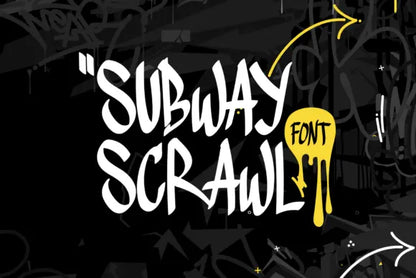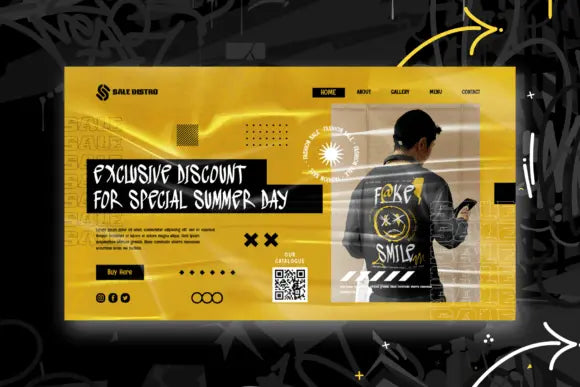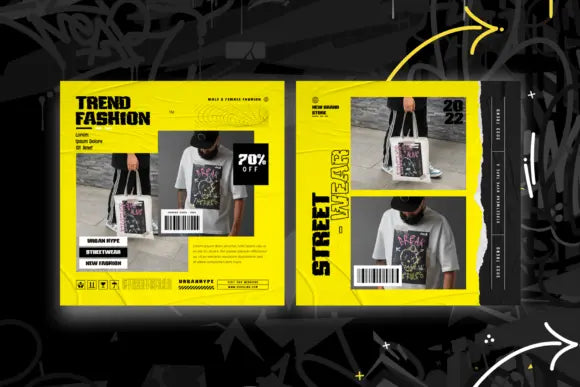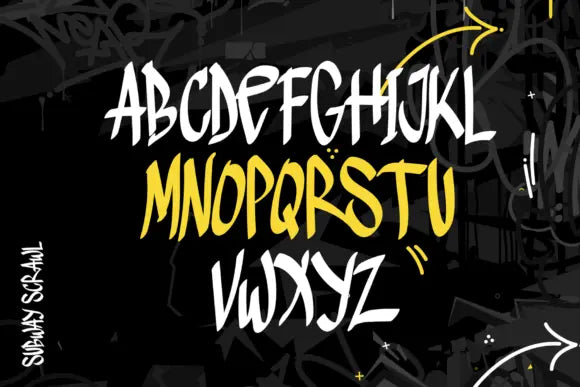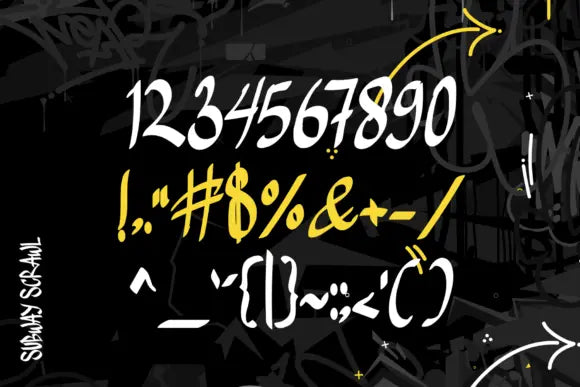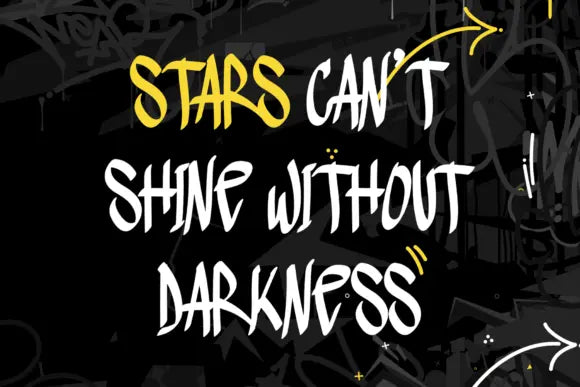
Fuente de garabatos de metro
Destaca en tus proyectos "Subway Scrawl", una fuente de graffiti de líneas delgadas, para yuxtaponer la sofisticación urbana con un estilo urbano sin filtros. Esta fuente minimalista, definida por líneas suaves e ininterrumpidas y un estilo urbano fresco, realza tus diseños al tiempo que conserva un auténtico espíritu de graffiti.
Una combinación espléndida para el arte callejero, carteles, marcas y todas las actividades creativas que requieren un componente tipográfico refinado pero atrevido, “Subway Scrawl” ofrece una estética moderna y única para garantizar que sus creaciones realmente destaquen.